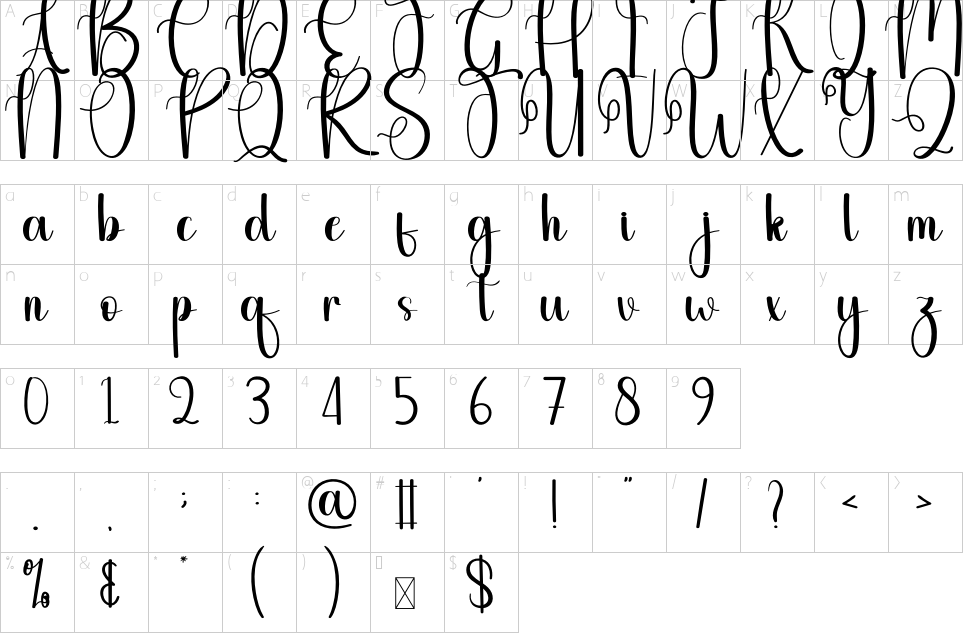
A fonte Autography é uma escolha óbvia para quem procura uma gráfica e natural para trabalhos em português. Desenvolvida pelo designer William Jhordy, ela traz um visual elegante e versátil, adequado para múltiplas aplicações. Seja para criar cartões de visita, textos para redes sociais ou até mesmo para uma capa de livro, a Autography oferece linhas sólidas e estilos bem definidos que garantem a legibilidade e a qualidade. Além disso, sua versão gratuita para Windows e Mac permite que você acesse e faça seu download facilmente, tornando-a uma excelente opção para quem busca uma fonte de qualidade sem precisar pagar uma taxa extra. Com 484 downloads, é claro que a Autography tem a capacidade de fazer um grande impacto em qualquer projeto.